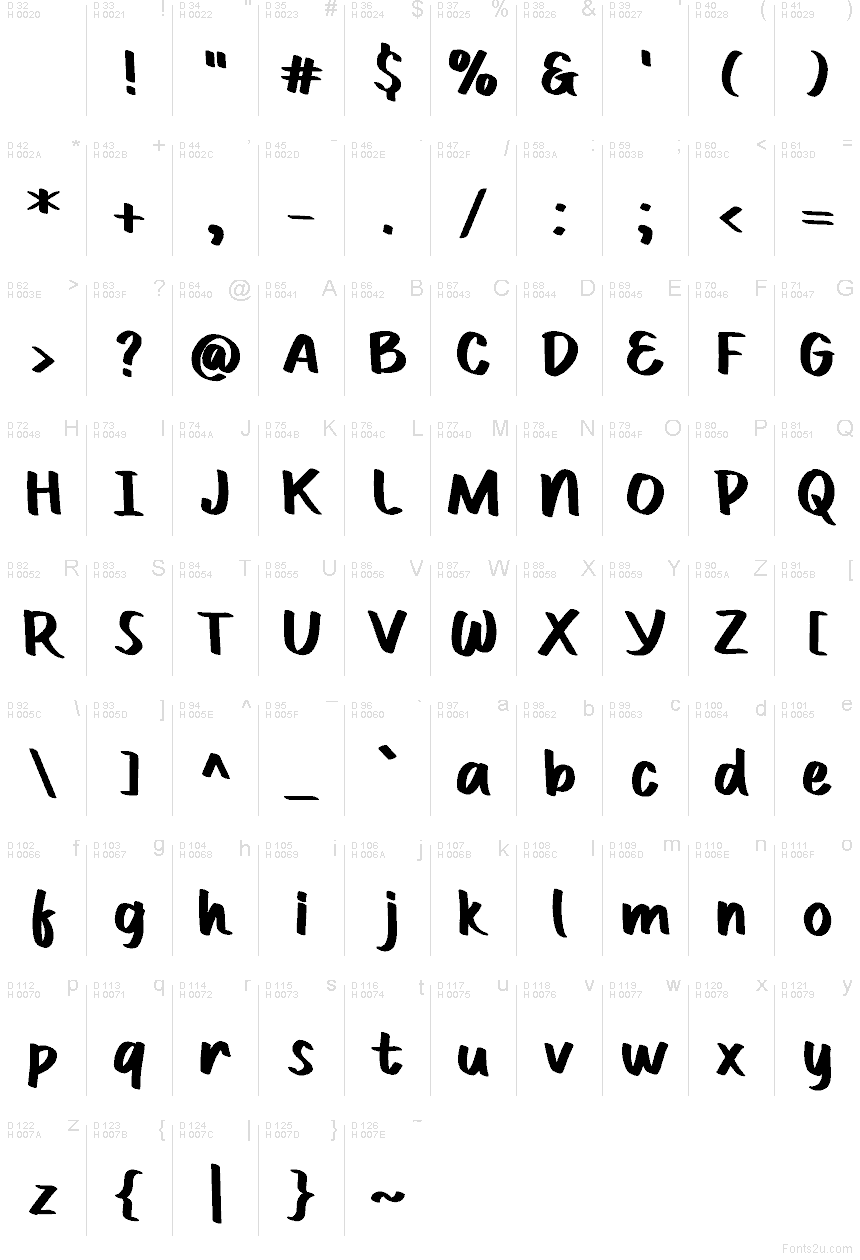
Down Join - це безкоштовний рукописний шрифт із широкими, округлими штрихами та невимушеним, плинним ритмом. Літери мають вигляд «живих», намальованих від руки, а не ідеально відшліфованих форм - м’які вигини, нерівні краї та компактність надають словам дружнього та неформального характеру.
Down Join чудово підходить для вітальних листівок, дизайну кав’ярень, етикеток товарів, заголовків на плакатах і графіки для соціальних мереж, оскільки поєднані форми роблять короткі написи живими й особистими. Він також вдало вписується в ескізи логотипів та упаковку, де потрібна рукописна естетика без натяку на неохайність.